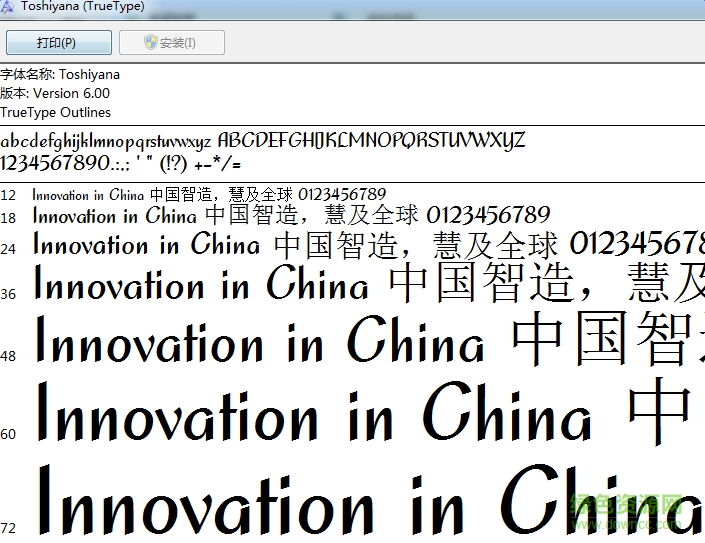
Toshiyana(漢儀西文字體)
Toshiyana字體是漢儀西文字體中的一款個(gè)性字體,該字體可以廣泛應(yīng)用于廣告設(shè)計(jì)、宣傳海報(bào)、ppt、影視制作以及任何使用文字的領(lǐng)域,有需要的朋友可以免費(fèi)下載收藏。
Toshiyana字體是一款極具個(gè)性的字體,該字體屬于漢儀希文字體五款中的其中一款,字體非常大方有勁道,給人大氣的感覺(jué)。歡迎來(lái)綠色資源網(wǎng)下載使用!